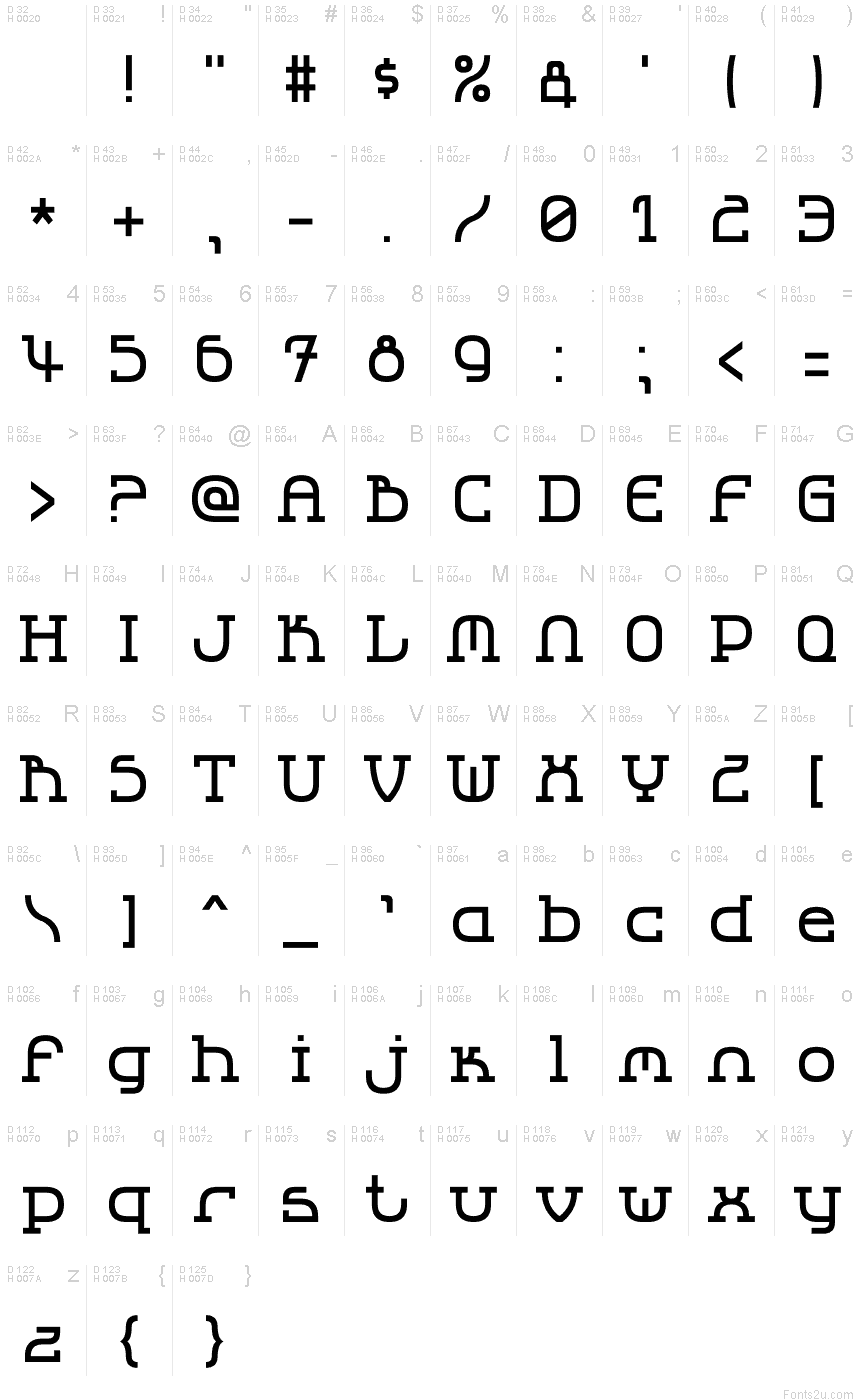
LBC Cool 2 to darmowy krój pisma typu display od LBC, wyróżniający się zaokrąglonymi, blokowymi kształtami i zwartą konstrukcją. Prezentuje się gładko i solidnie, a proste, obłe formy nadają mu graficzny, niemal szyldowy charakter, unikając zbędnego zdobnictwa.
LBC Cool 2 świetnie sprawdza się w nagłówkach plakatów, logotypach, naszywkach i krótkich tekstach promocyjnych, gdzie pogrubione, zaokrąglone litery stanowią główny punkt projektu. Ten darmowy font pasuje również do grafik eventowych i akcentów wizualnych, szczególnie gdy potrzebujesz zwartego, technicznego wyglądu zamiast tradycyjnego kroju szeryfowego.
LBC Cool 2